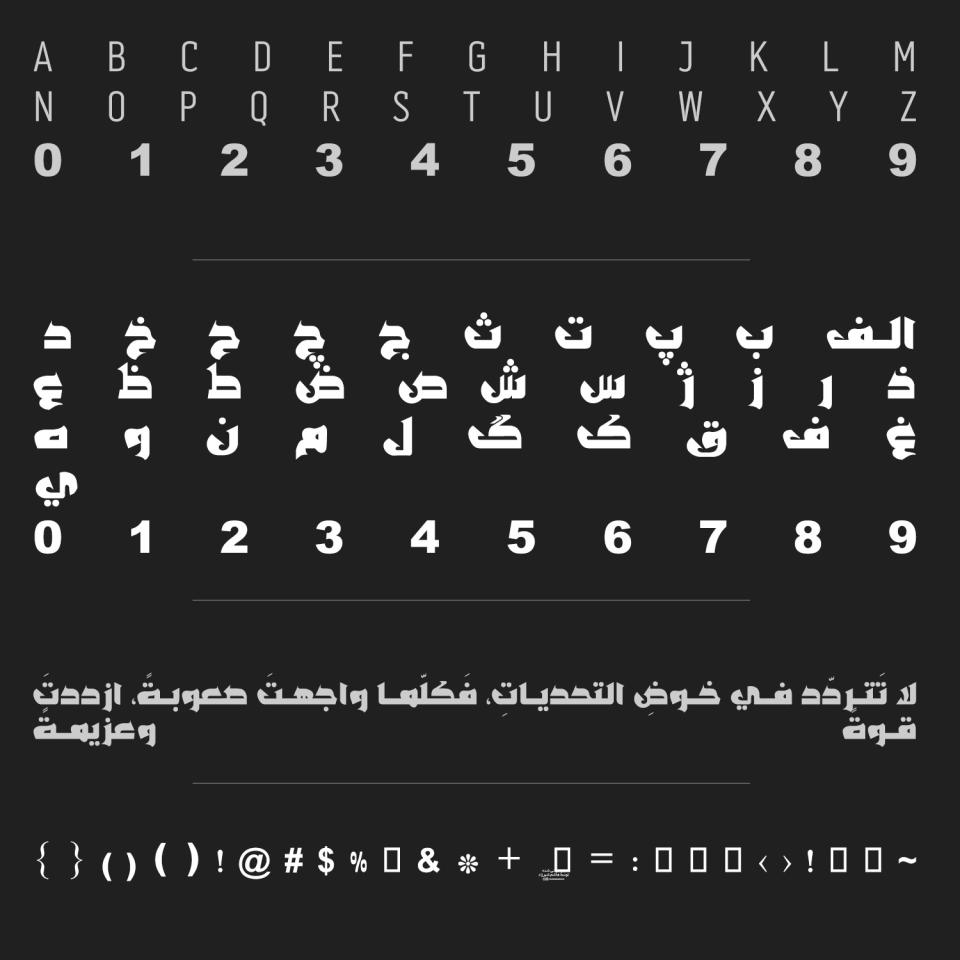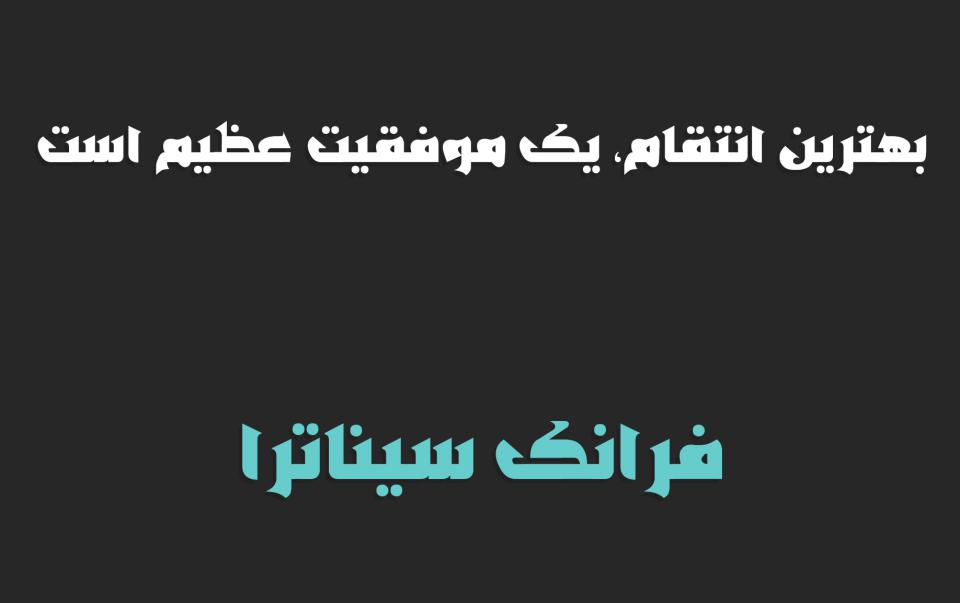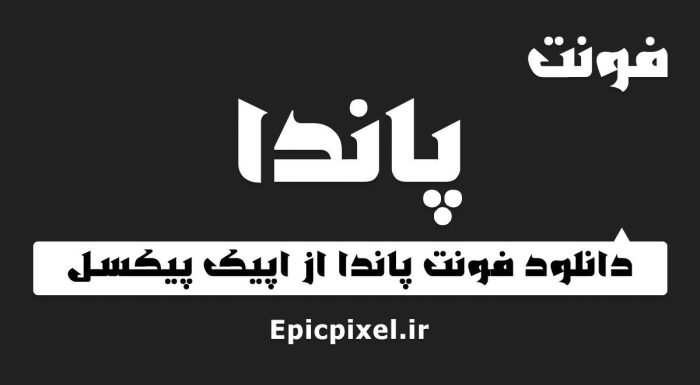
فونت پاندا فارسی Panda
فونت پاندا، یک انتخاب جذاب برای کسانی است که به دنبال تنوع و زیبایی در نوشته های خود هستند. این فونت با طراحی فانتزی و منحصربه فردش، حس صمیمیت و خودمانی بودن را به مخاطب القا می کند. اگرچه شاید برای متن های طولانی و رسمی چندان مناسب نباشد، اما در عوض، برای عناوین کوتاه، کارت پستال ها، طرح های گرافیکی و به ویژه محتوای شبکه های اجتماعی، گزینه ای ایده آل به شمار می رود.
یکی از ویژگی های برجسته فونت پاندا، خوانایی بالای آن در اندازه های مختلف است. این یعنی چه در ابعاد کوچک و چه در ابعاد بزرگ، نوشته ها به راحتی قابل خواندن هستند و چشم را خسته نمی کنند. همچنین، طراحی حروف این فونت به گونه ای است که حس شادی و سرزندگی را منتقل می کند و می تواند به جذابیت بصری طرح های شما بیافزاید.
با وجود ظاهر فانتزی، فونت پاندا از ساختار استانداردی پیروی می کند که باعث می شود با اکثر نرم افزارها و سیستم عامل ها سازگار باشد. این یعنی بدون نگرانی از بهم ریختگی متن، می توانید از آن در پروژه های مختلف خود استفاده کنید. در کنار تمام این مزایا، باید به این نکته هم اشاره کرد که به دلیل طراحی خاص، شاید این فونت برای هر نوع محتوایی مناسب نباشد و بهتر است در جای درست و متناسب با حال و هوای متن مورد استفاده قرار گیرد. اما در کل، اگر به دنبال فونتی هستید که به نوشته های شما جلوه ای متفاوت و دوست داشتنی ببخشد، فونت پاندا یک انتخاب عالی و رایگان است.